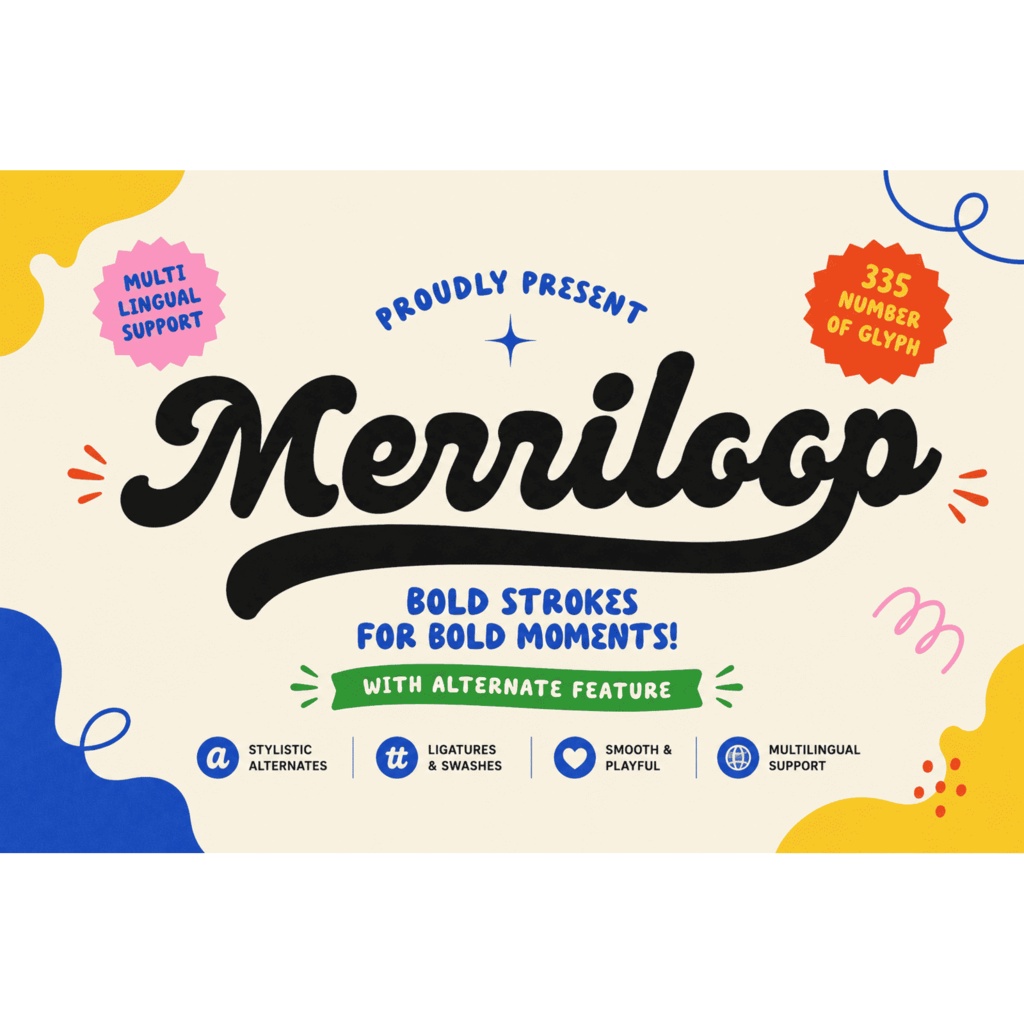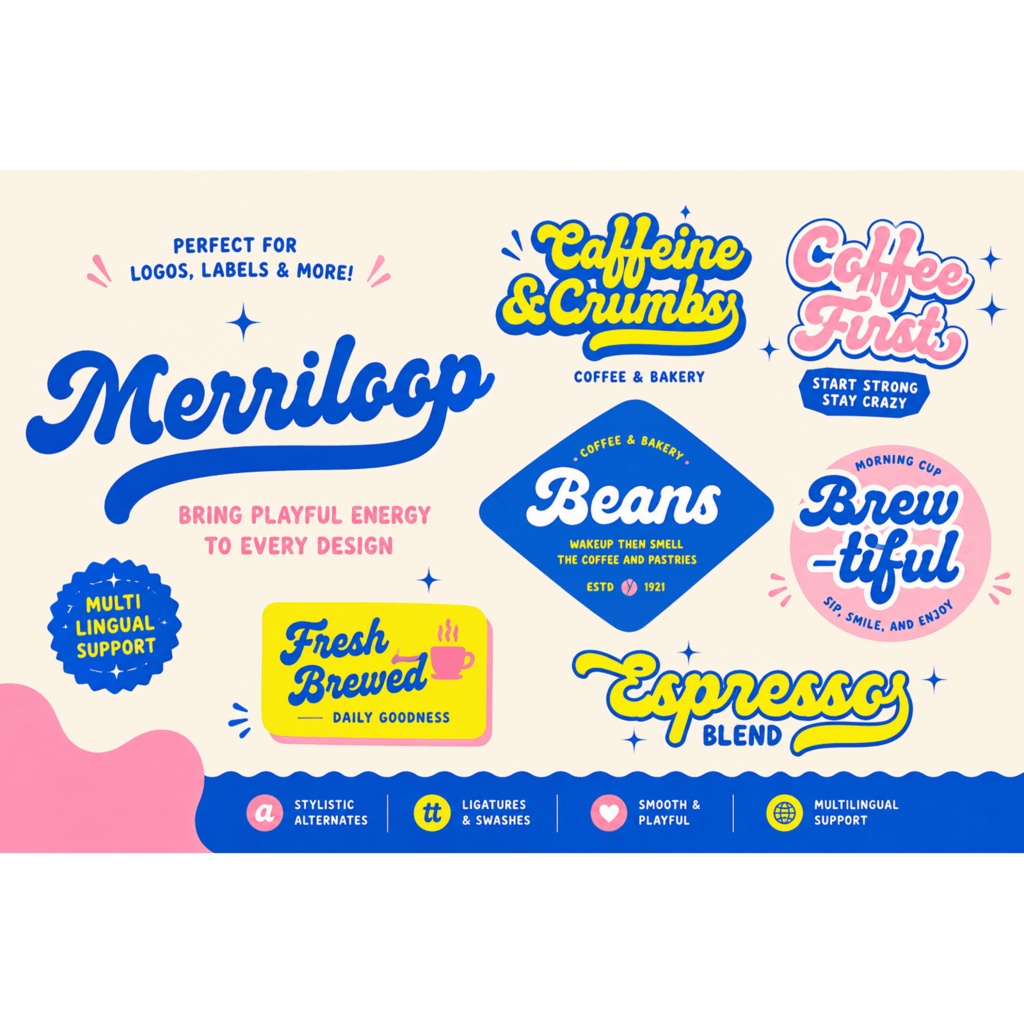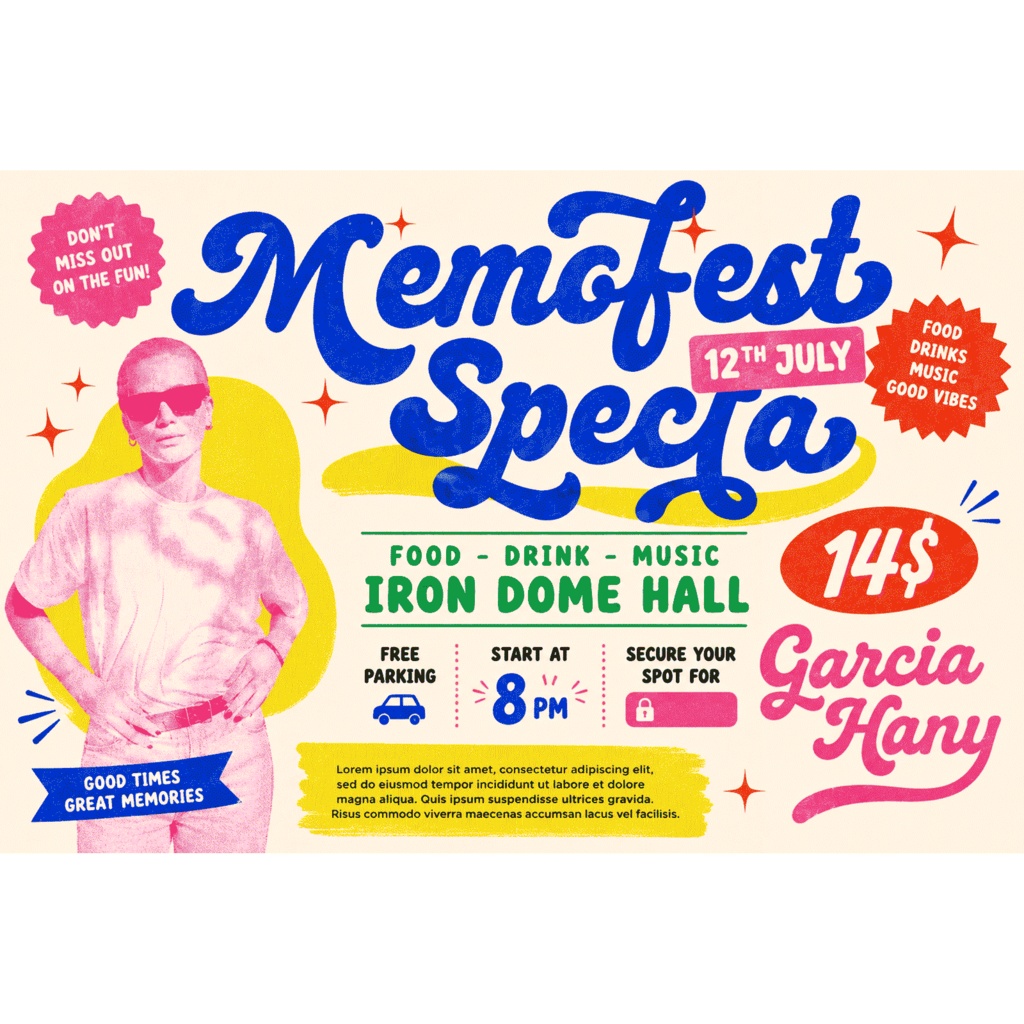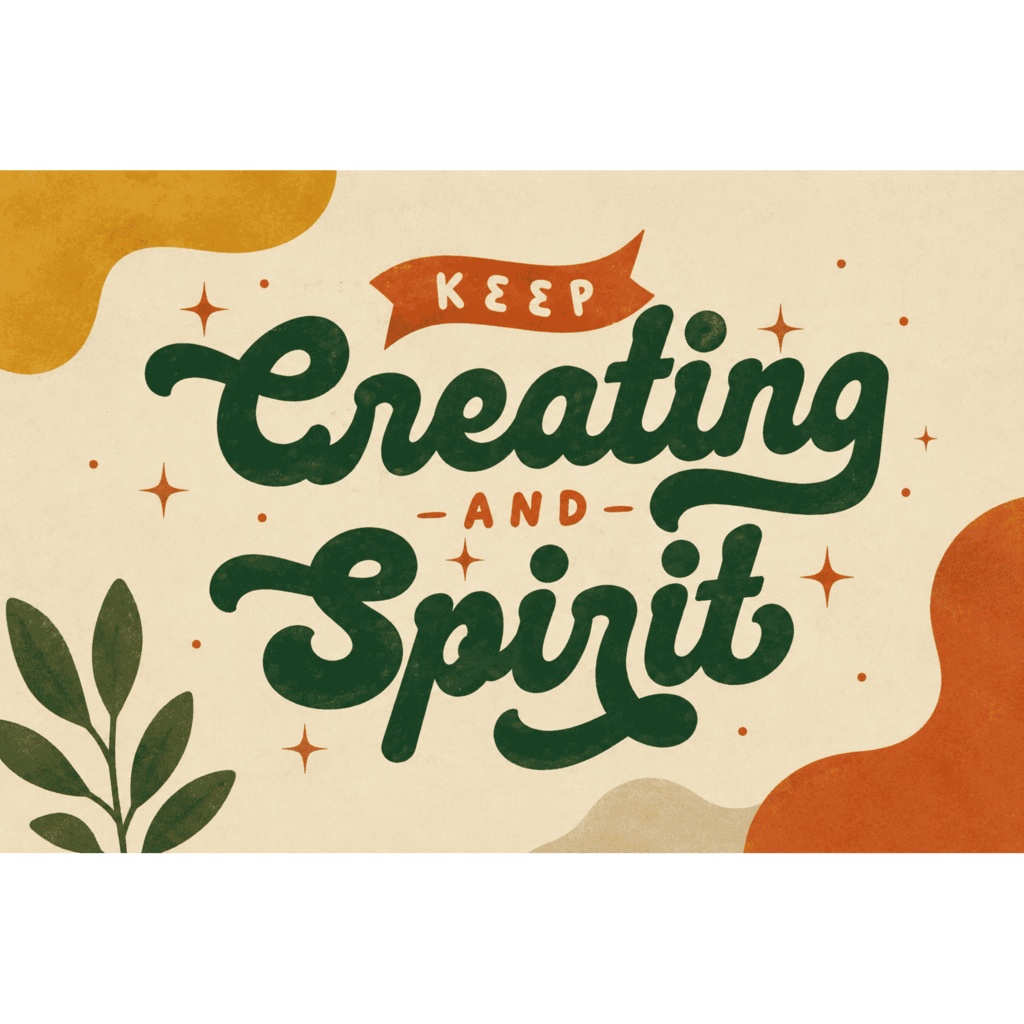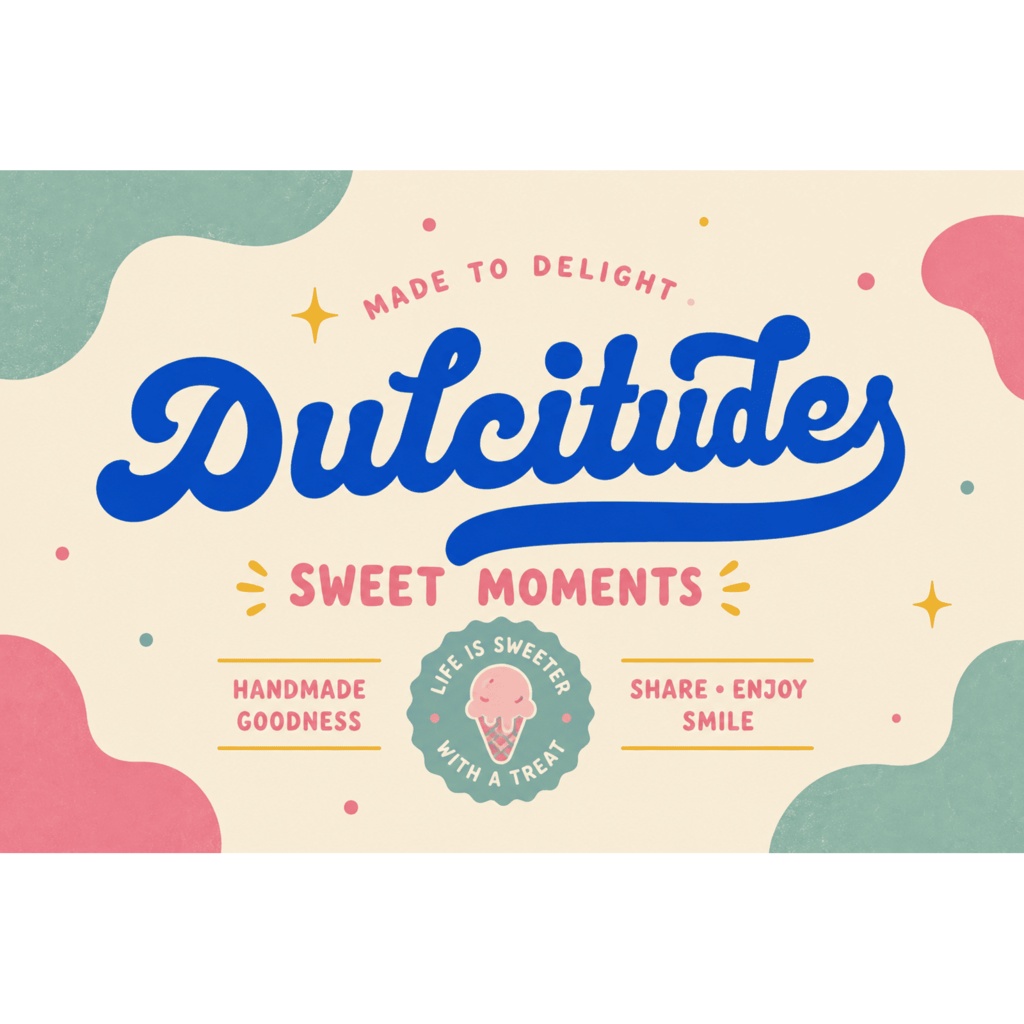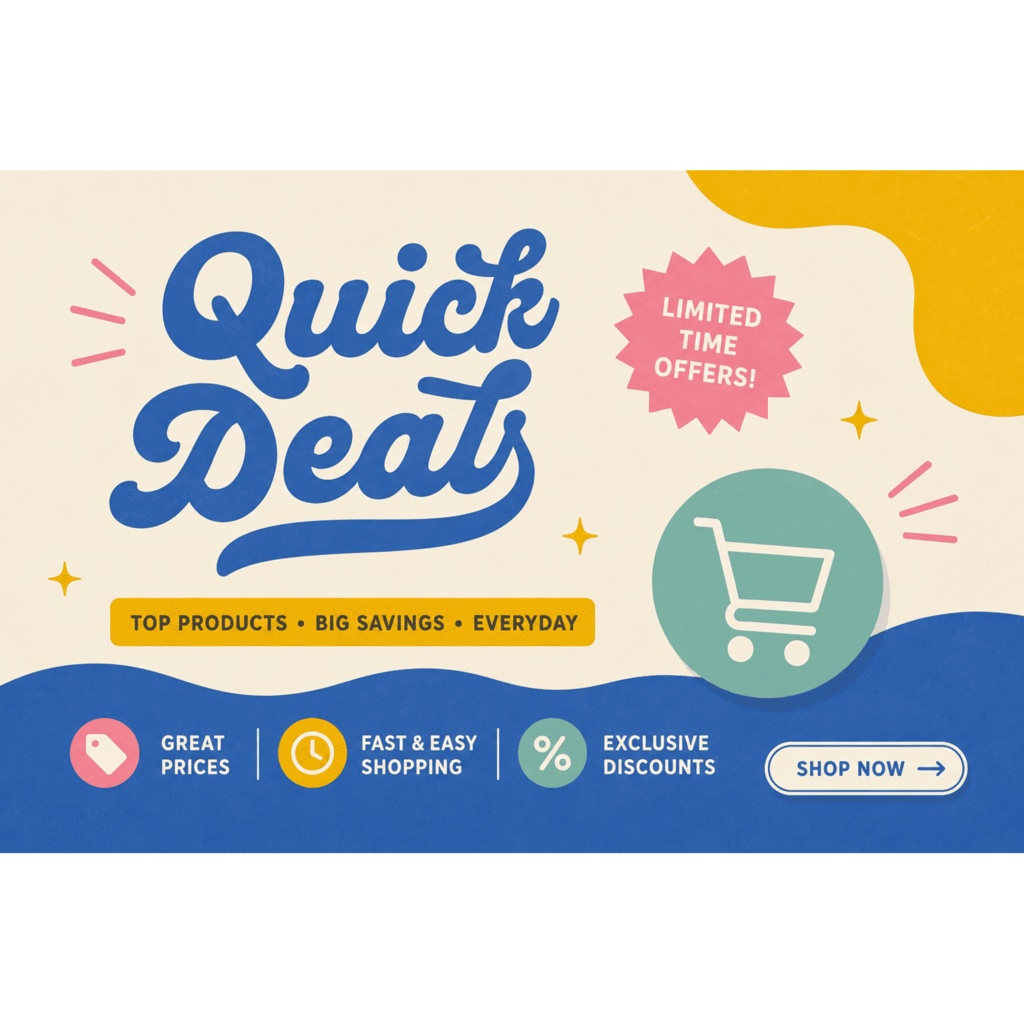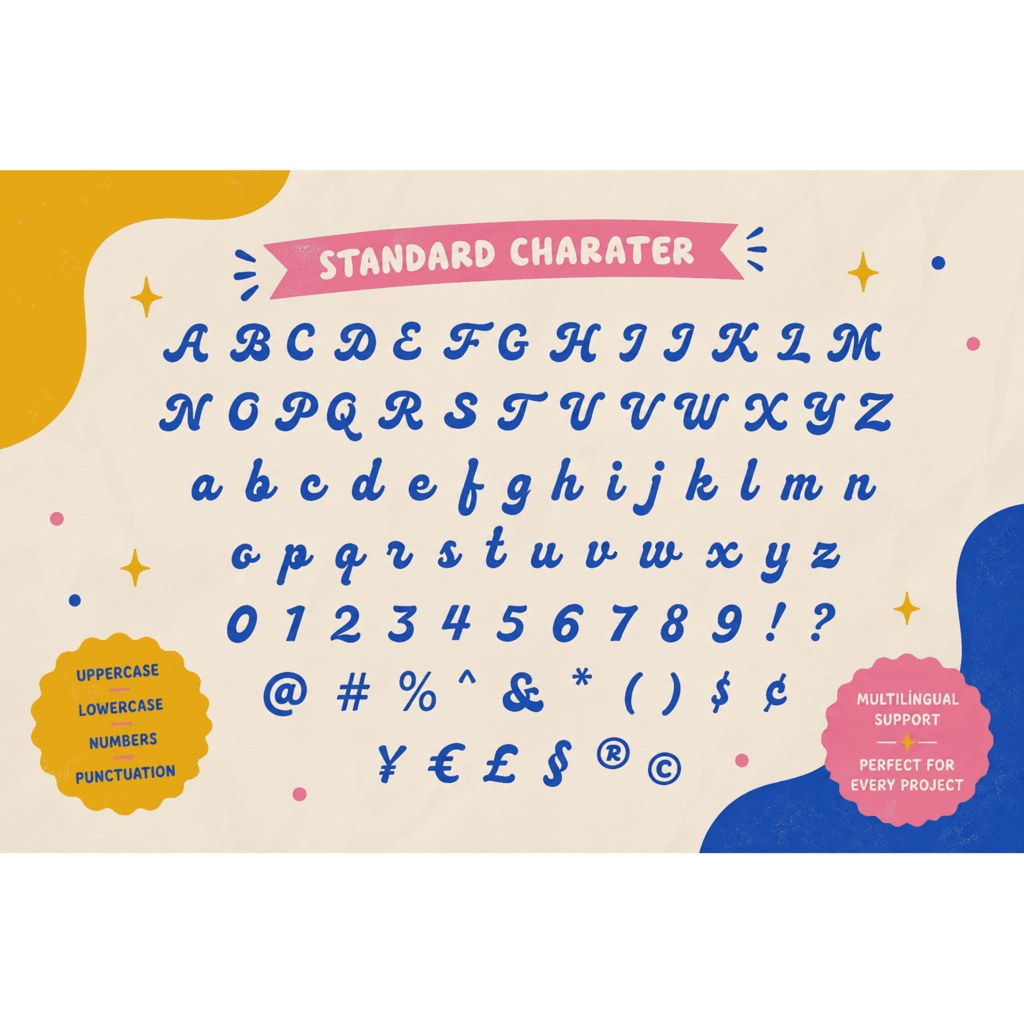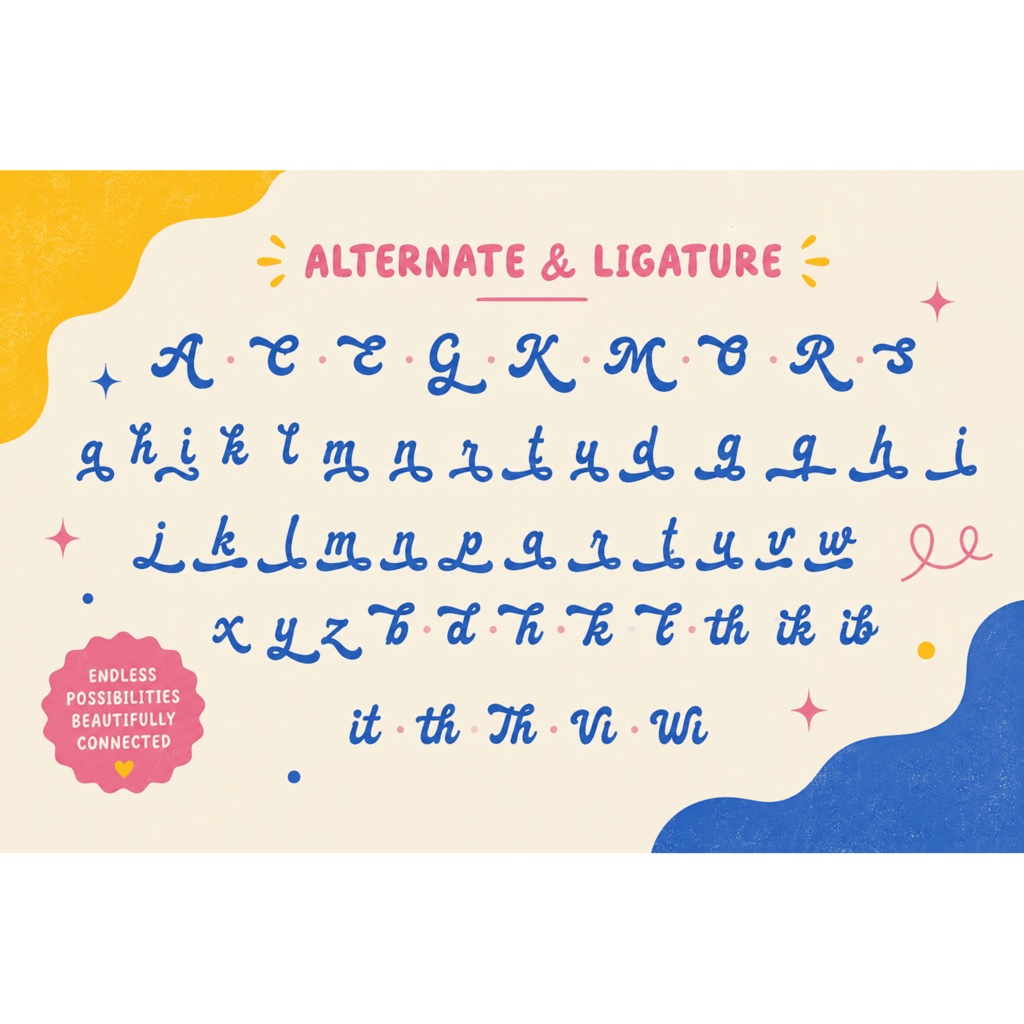
Merriloop | レトロな筆記体フォント / Retro Script Font | ロゴ・看板・サムネイル素材
Merriloop(メリーループ)は、1960〜70年代のサインペイント(手描き看板文字)を思わせるボールドなレトロ筆記体フォントです。丸みのある繋がり文字と、遠くからでも読めるしっかりした視認性が特徴で、ロゴ、看板・サイン、パッケージ、ポスター、Tシャツ、マグカップ、ヴィンテージ/レトロ系ブランディングに最適なディスプレイ用英字フォントです。 Merriloop is a bold retro script font inspired by hand-painted 60s–70s sign-painting lettering — rounded, connected forms with strong visual weight and a friendly, hand-lettered personality. Built as a single Regular style display typeface, it is ready for logos, signage, packaging, posters, t-shirts, mugs, and vintage/retro branding projects. 収録内容 / Included - 1 style (Regular) — 4 formats: OTF / TTF / WOFF / WOFF2 (Merriloop-Regular) - 305 glyphs - OpenType features: stylistic sets ss01–ss03, contextual/stylistic alternates (aalt, salt), swash characters (swsh), ligatures (liga), and kerning (GPOS kern) 対応文字 / Character Set - Basic Latin(A–Z・a–z・数字・記号)+ Western European Latin (Latin-1) accents - 日本語・かな・漢字は含まれません。Cyrillic / Greek glyphs are also NOT included — this is a Latin-only typeface. - スワッシュ・オルタネートは OpenType 対応アプリ(Photoshop / Illustrator など)の字形パネル/スタイルセットから切り替えます(PUA 文字コードではありません)。 用途 / Uses - ロゴ・ワードマーク (logos & wordmarks) - 看板・店舗サイン・サインペイント風デザイン (signage & storefronts) - パッケージ・ラベル (packaging & labels) - ポスター・ポップ・見出し (posters & display headlines) - Tシャツ・アパレル・マグカップなどのグッズ (t-shirts, apparel, mugs & merchandise) - ヴィンテージ/レトロのブランディング、SNS画像、配信サムネイルのタイトル文字 (vintage branding, social graphics, streamer thumbnail titles) 形式 / Formats - Merriloop-Regular.otf / Merriloop-Regular.ttf (desktop print & design apps) - Merriloop-Regular.woff / Merriloop-Regular.woff2 (web via @font-face) 対応環境 / Compatibility - Windows / macOS, Adobe Photoshop / Illustrator / InDesign, Affinity, Figma, Canva, Procreate, Cricut Design Space, Silhouette Studio, and any application that reads OTF/TTF; web projects via WOFF/WOFF2. 利用許諾 / License - 本コピー作成のスコープ外のためライセンス条項は未記載です(出品前にライセンスを確認・記載してください)。License terms pending user — not stated in this copy-only run. 更新 / Notes - Font name, single Regular style, 305-glyph Latin-only coverage, and OpenType feature set verified from `outputs/font-preparation/merriloop/` (audit-report.md, description.md). Copyright (c) 2026 PaperMoon. - 2026-08-20: Tag set expanded from 20 to 30 with 10 live-validated new tags (書体・フォント, 良いフォント, ロゴデザイン, ディスプレイフォント, フォントダウンロード, OpenType, フォントデザイン, 英字フォント, タイポグラフィ, フォント デザイン).